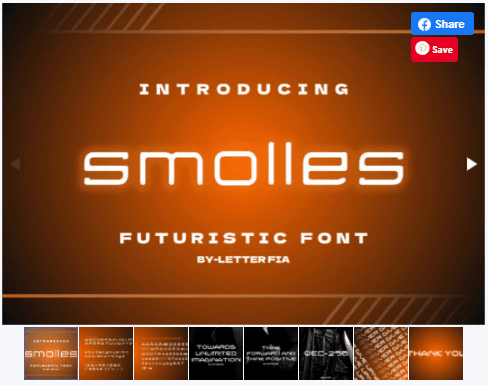
Smolles Font
Smolles - это классный футуристический шрифт без засечек. Его можно легко сопоставить с невероятно большим набором проектов, поэтому добавьте его к своим творческим идеям и обратите внимание, как они выделяются среди них!